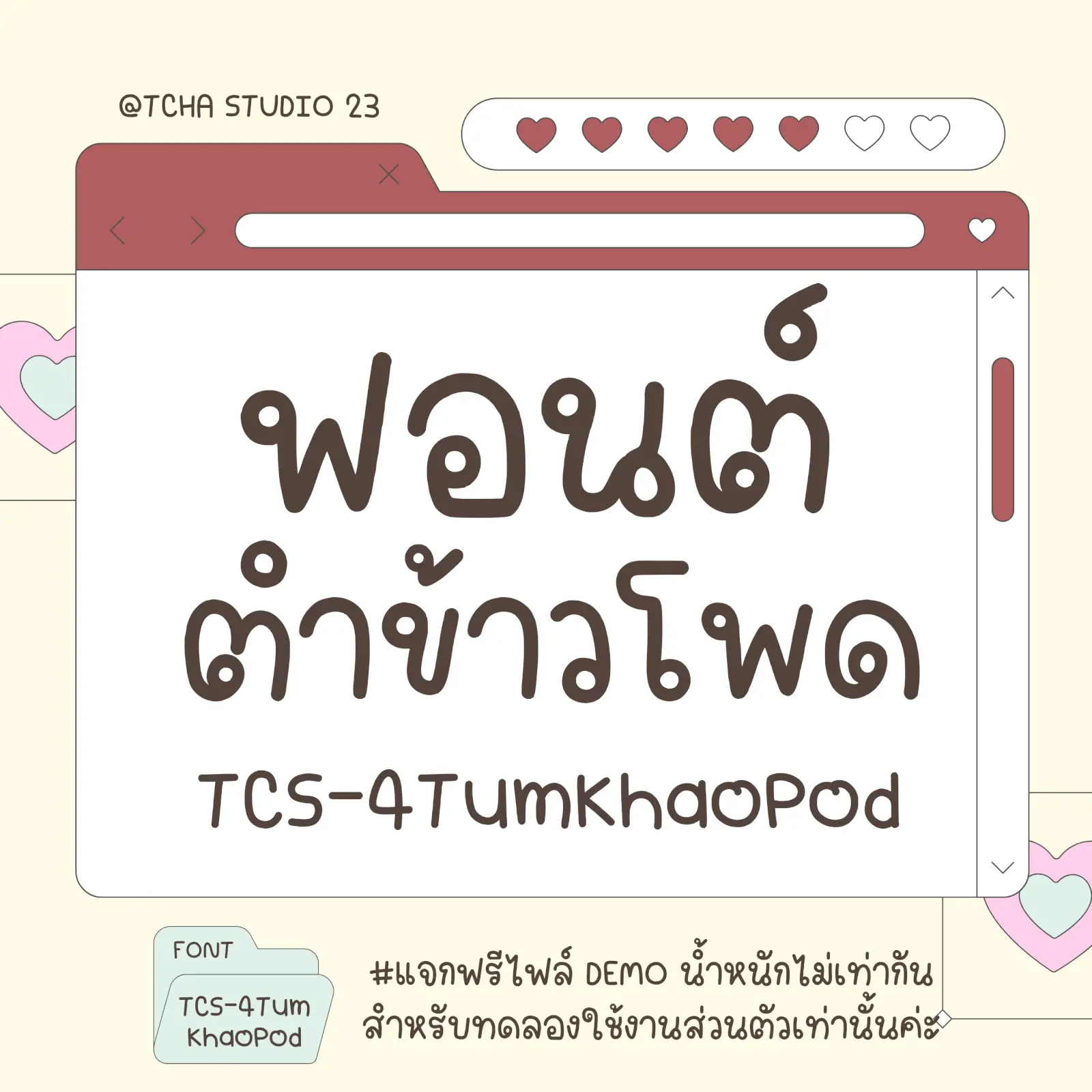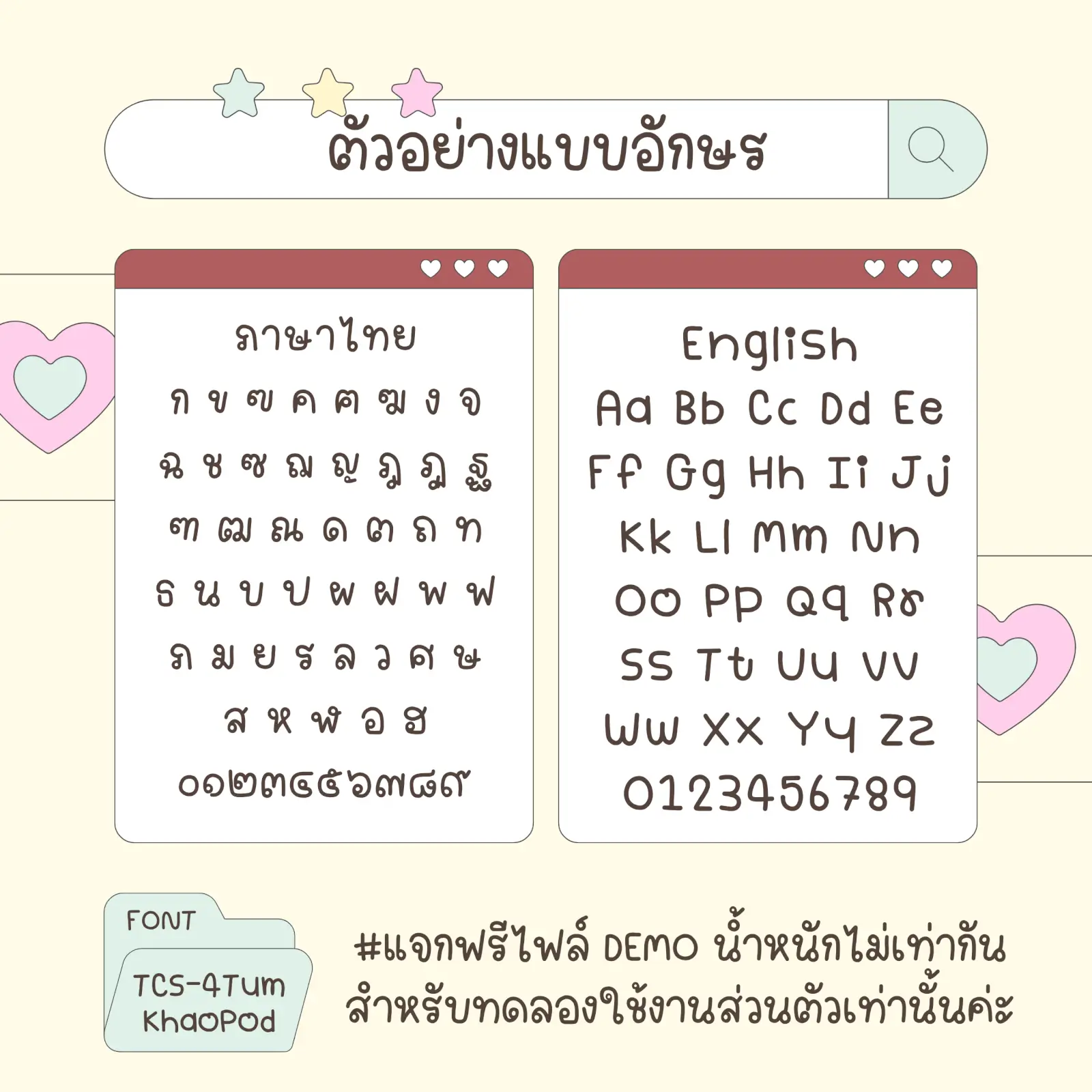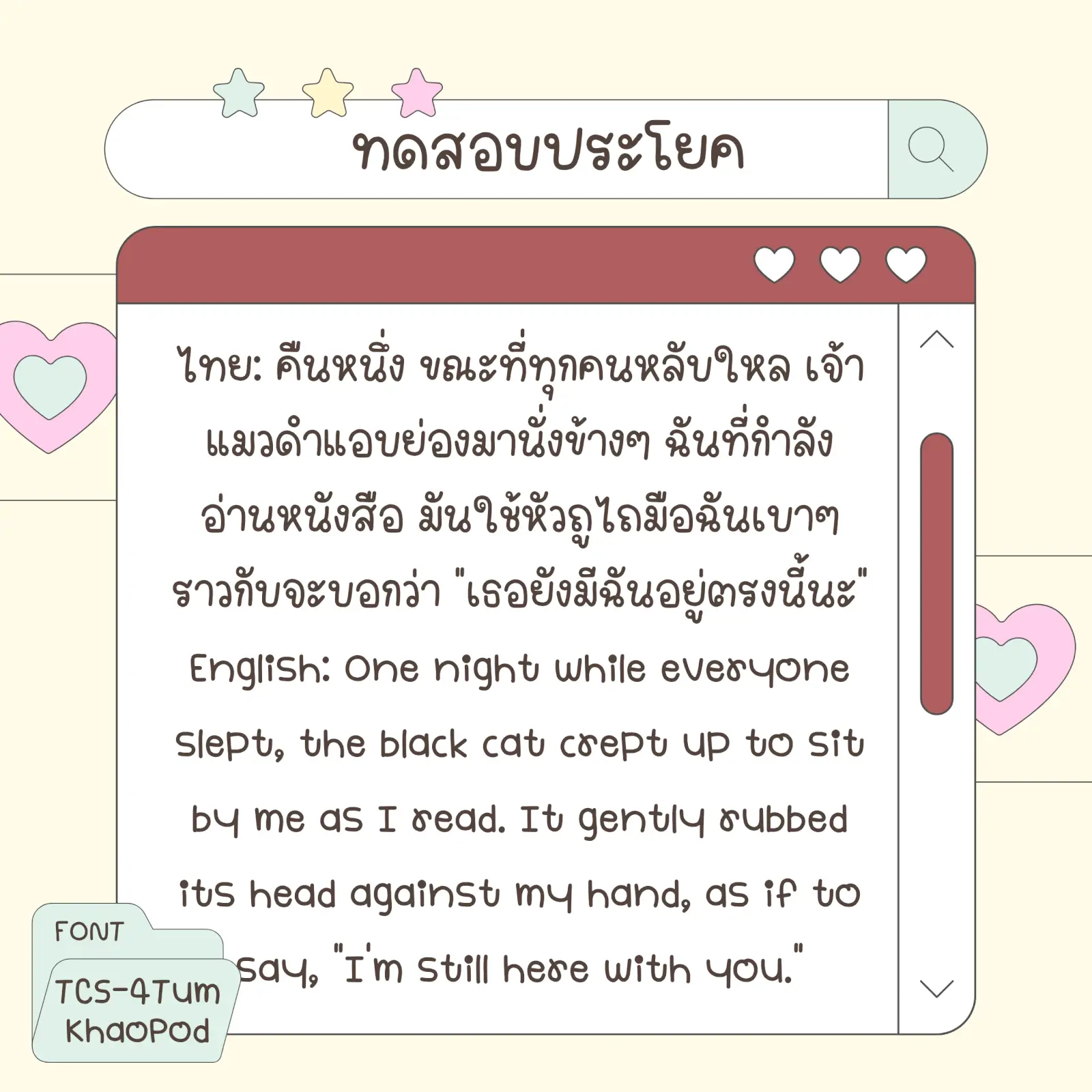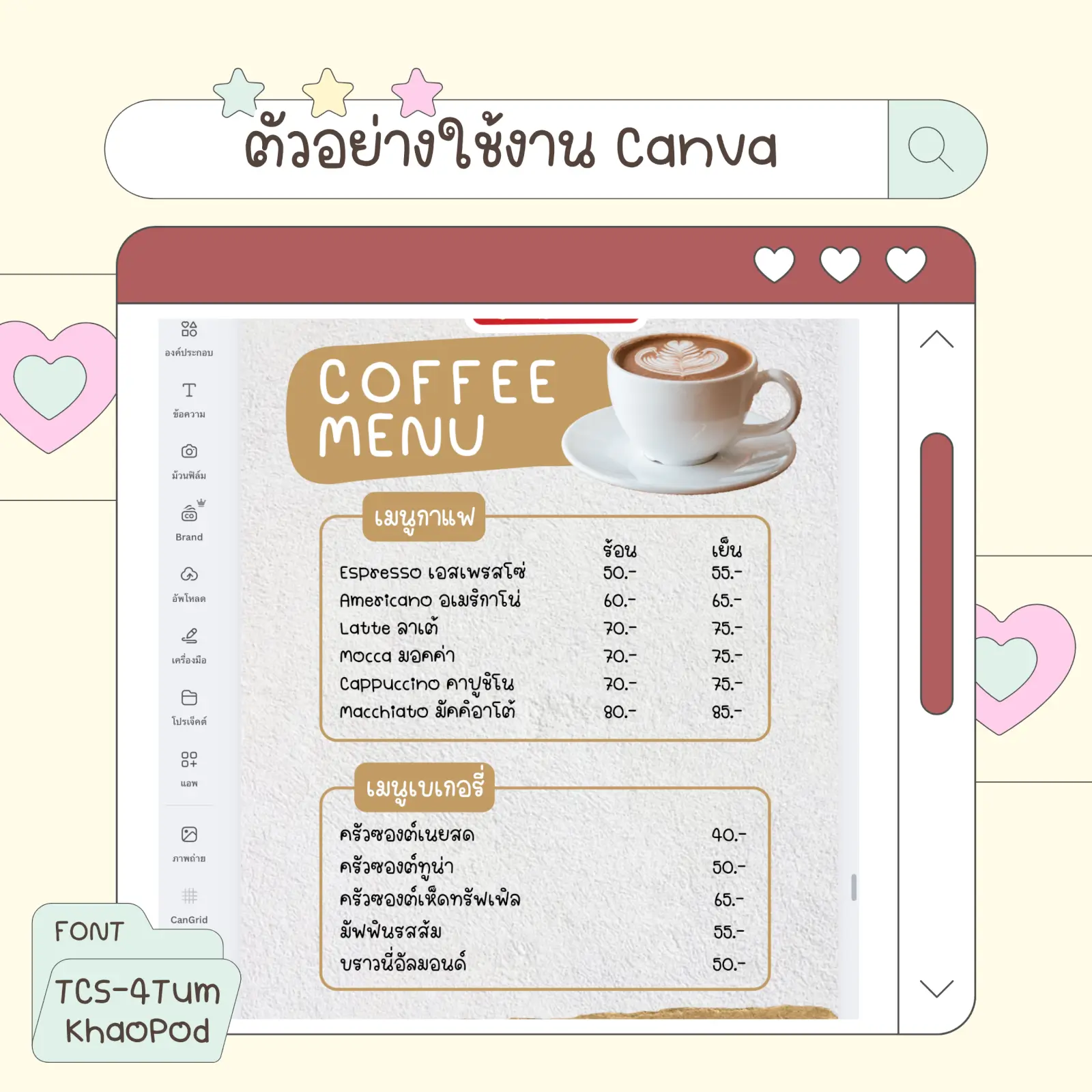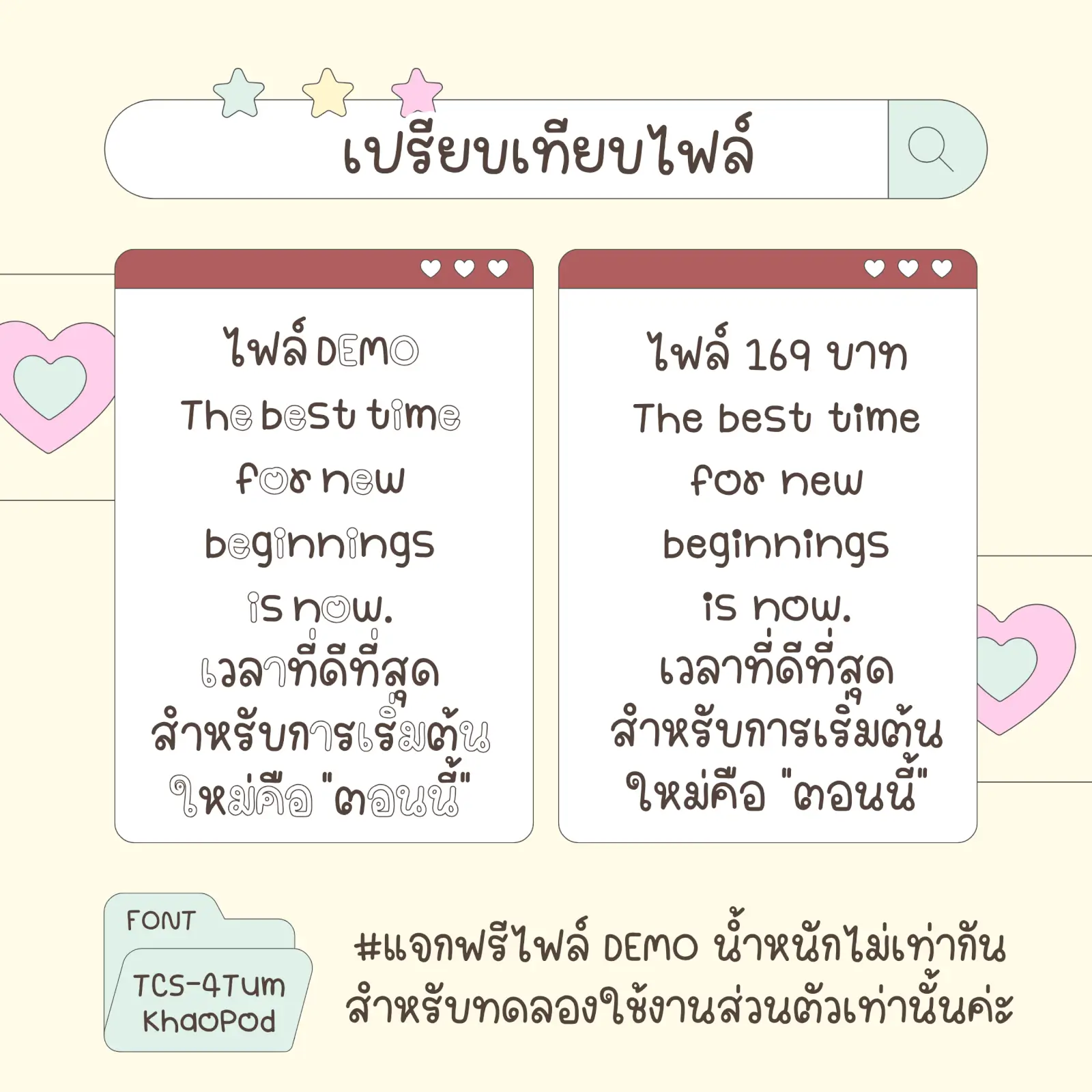
ฟอนต์ตำข้าวโพด (TCS4TumKhaoPod) – โหลดฟรี เวอร์ชันทดลอง (Demo) สำหรับทดลองใช้ส่วนตัวเท่านั้น
- มีน้ำหนักไม่เท่ากัน ยังไม่ปรับสระ
ตำข้าวโพด (TCS4TumKhaoPod)